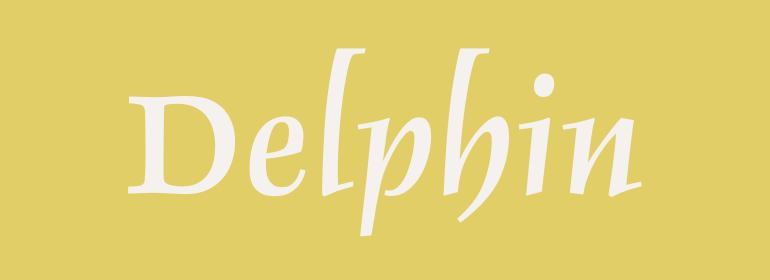
Delphin®
Delphin®,这款字体结构工整、笔画清晰,兼顾美观与易读性,适用于标题、正文、海报、包装、LOGO 等多种场景。字形优雅稳定,风格百搭耐看,适配日常排版与创意设计,让文字呈现更舒适、更具质感。Delphin®一笔一画,皆是细节,以均衡的比例、流畅的线条打造舒适视觉体验,字形端正大气,风格简约现代。无论是商业设计、品牌宣传还是日常排版,都能轻松驾驭,让文字更有格调与力量。Delphin®字体下载。